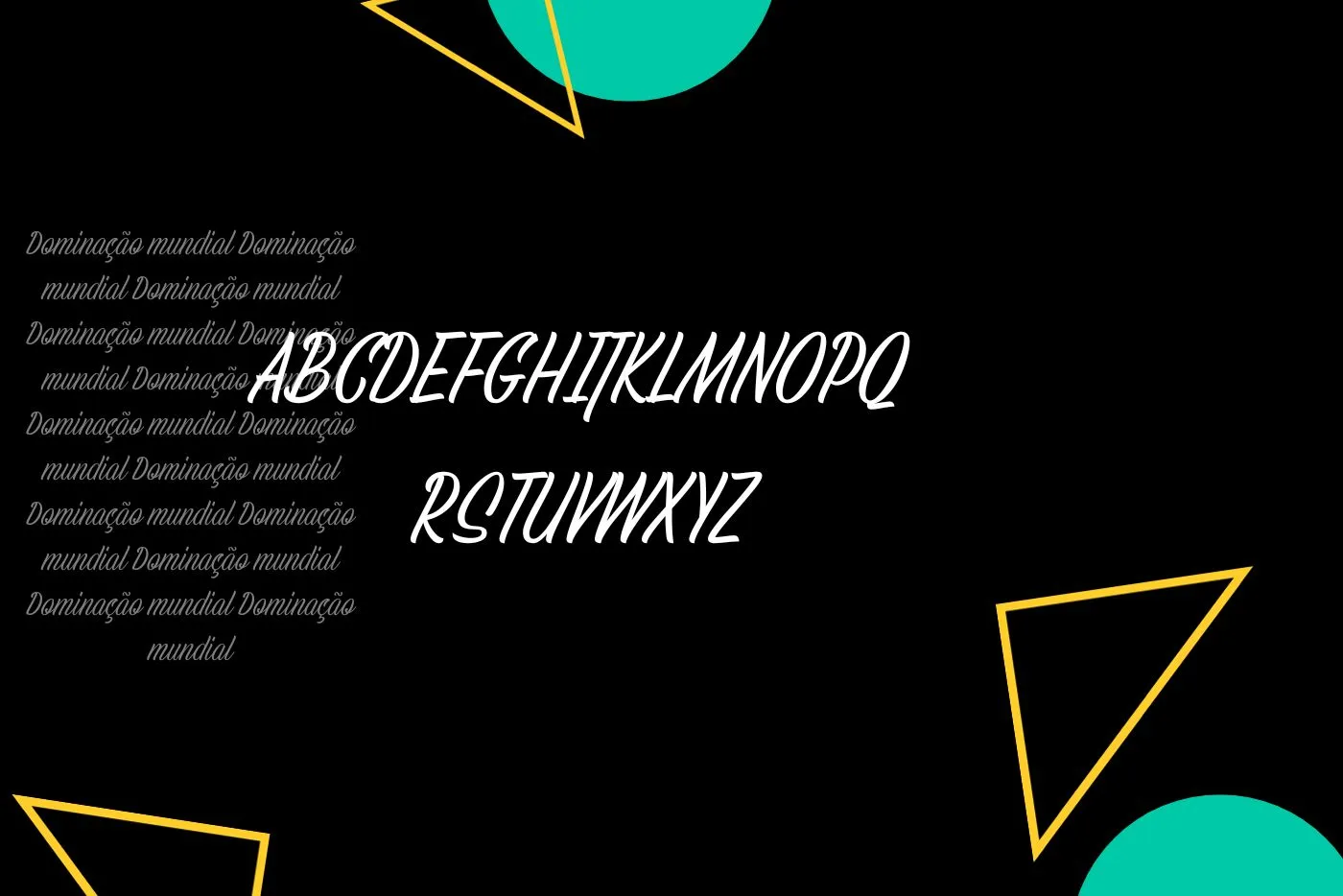
A fonte Nagamaki Script é uma fonte manuscrita que evoca uma sensação de elegância e caligrafia. Com seus traços fluidos e orgânicos, essa fonte tem um charme único que a torna adequada para uma variedade de aplicações de design. Seu estilo manuscrito é inspirado em letras cursivas, o que o torna perfeito para projetos que buscam transmitir sofisticação e personalização.
Sua beleza está em sua versatilidade. Ele pode ser usado em convites de casamento, cartões comemorativos, logotipos de marcas de luxo e muito mais. Seu toque artesanal e sua aparência manuscrita transmitem uma sensação de autenticidade, tornando-o uma escolha popular para projetos que buscam um toque humano. Você também pode utilizar a Fonte Angolia, que é mais próxima desta família de fontes.
Além disso, oferece uma variedade de caracteres e traços alternativos que permitem criar designs únicos e personalizados. Isso o torna uma escolha popular para designers gráficos e artistas que desejam adicionar um toque especial aos seus projetos. Com suas linhas fluidas e estilo charmoso, ela é uma escolha versátil para designers que buscam dar um toque de classe ao seu trabalho.
Elegância e Sofisticação da Fonte Nagamaki Script
É um exemplo notável de elegância e sofisticação no mundo da tipografia. Com seus traços suaves e fluidos, esta fonte manuscrita transmite uma sensação de refinamento e charme. Cada personagem parece ter sido cuidadosamente desenhado por um calígrafo habilidoso, tornando-o uma escolha perfeita para projetos que buscam uma estética elegante e personalizada. Para usos mais avançados, é necessário utilizar a fonte Becca e Perry fazendo uma combinação com esta família.
Seu estilo manuscrito é especialmente adequado para aplicações de design que exigem um toque artesanal. Seus caracteres são desenhados com graça e fluidez, criando uma sensação de autenticidade que muitas outras fontes não conseguem capturar. Uma característica que contribui para a elegância desta fonte são os traços ornamentais e traços que a acompanham.
Família de Fontes Nagamaki Script
- Nagamaki Script Regular
Quem é o designer da fonte Nagamaki Script?
A fonte Nagamaki Script é uma fonte manuscrita que evoca uma sensação de elegância e caligrafia e foi desenhada por Ivana Maric.